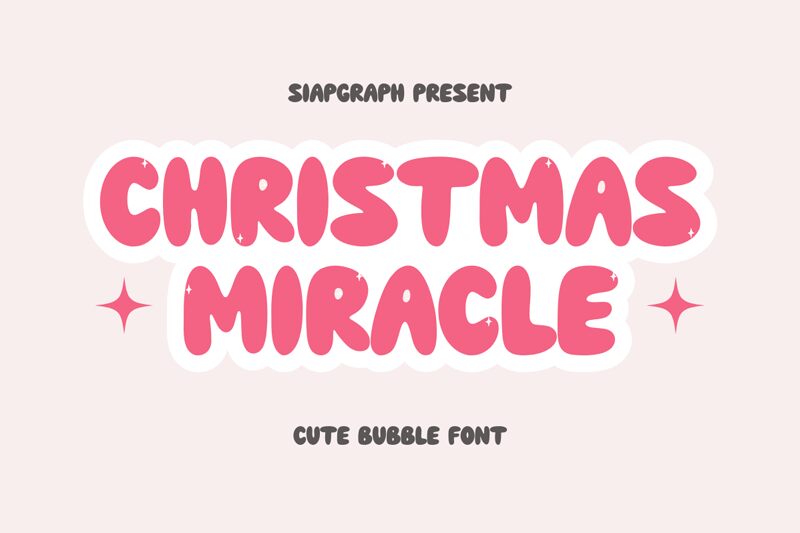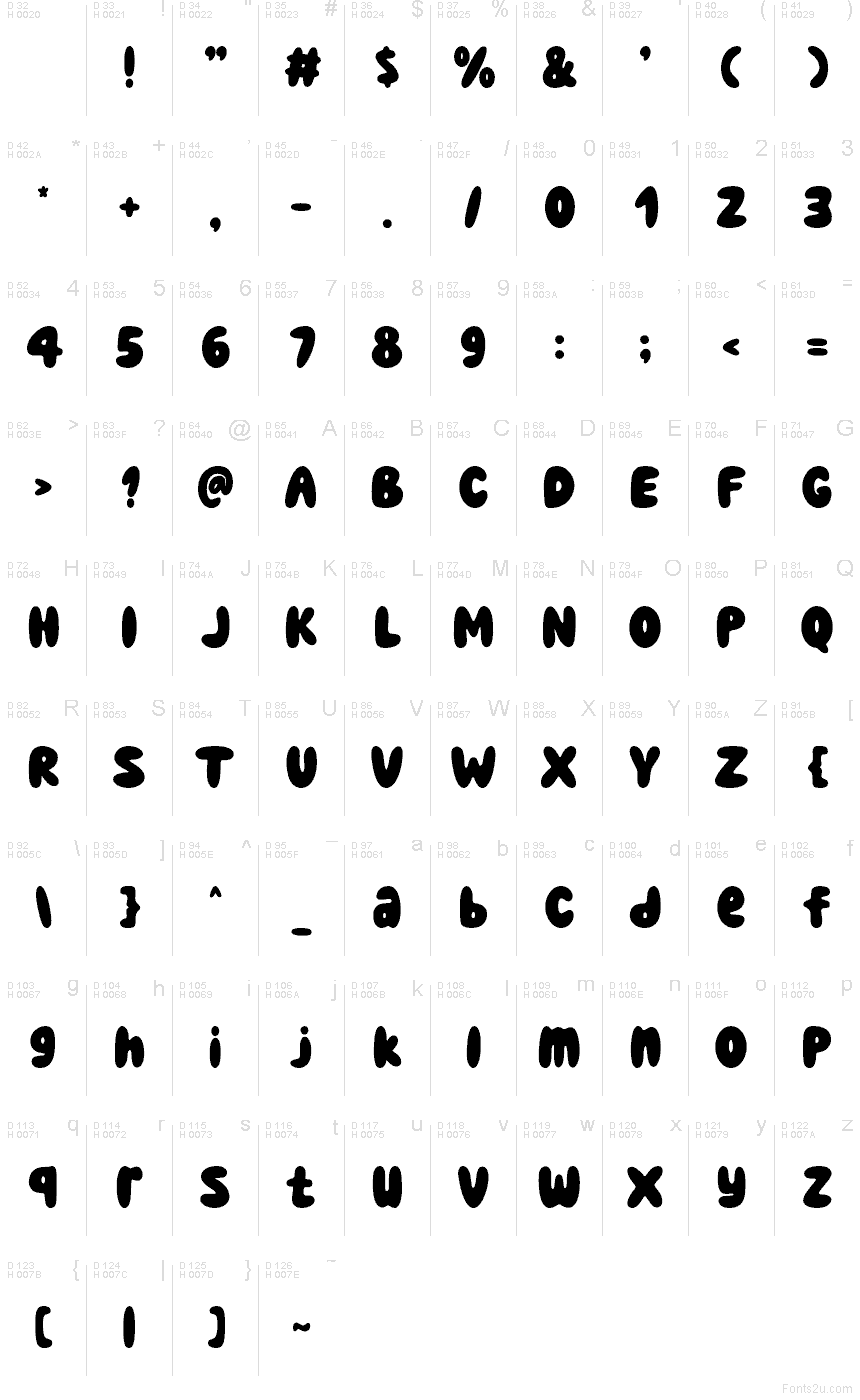
Christmas Miracle, bezpłatny krój pisma w stylu cartoon od SIAPGRAPH STUDIO, wykorzystuje obłe, zaokrąglone kształty, dzięki którym litery wydają się miękkie i niemal napuchnięte. Zwarte, pionowe formy tworzą rytmiczną całość, sprawiając, że font czyta się bardziej jak zestaw zabawnych kształtów niż standardowy krój displayowy.
Ta puszysta forma nadaje krótkim nagłówkom wyrazistości na zaproszeniach na przyjęcia dla dzieci, etykietach prezentowych, zestawach naklejek, opakowaniach produktów piekarniczych czy wesołych postach w mediach społecznościowych. Świetnie sprawdza się również w szkolnych dekoracjach czy w brandingu zabawek, gdzie miękkie kształty zachowują przyjazny, graficzny charakter, nie stając się przy tym niechlujnym pismem odręcznym.